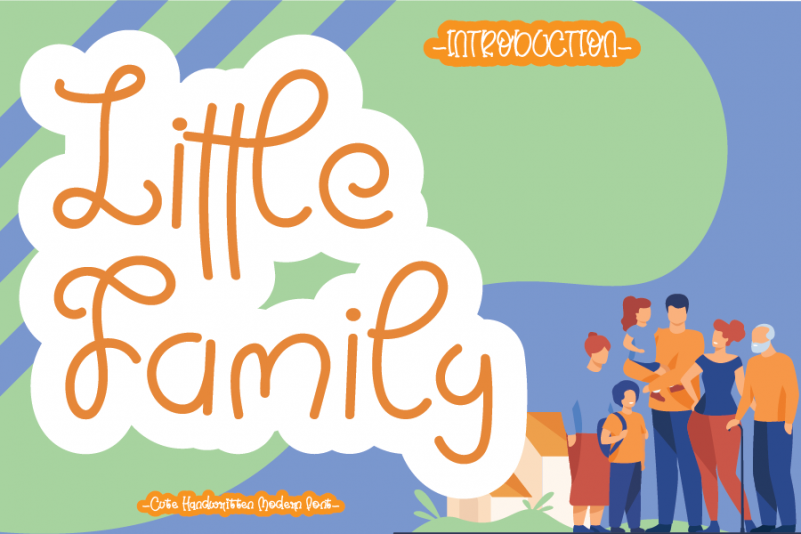
Little Family Font – Download Grátis
A Little Family Font é uma elegante fonte à mão escrita ideal para projetos criativos. Ela se destaca pelo seu aspecto acolhedor, charmoso e descontraído, características que garantem um toque único a cada projeto. Composta por traços leves e suaves, esta fonte é perfeita para quem busca uma mão escrita delicada e confortável. Ela pode ser usada em diversos contextos, como design editorial, publicidade ou até mesmo gráficos pessoais, dando ao seu trabalho um toque de personalização especial. A designer, handwrittenwanda, destaca-se pela criatividade e versatilidade desta fonte. Seja para expressar amor pelos familiares em cartões de aniversário, para dar vida a sua própria identidade visual ou até mesmo para criar cartazes divertidos na festa de um aniversário infantil, esta fonte se destaca como uma opção incrível e única para qualquer projeto que você possa imaginar. Experimentar o Little Family Font é garantir um toque diferenciado e pessoal em todos os seus projetos.